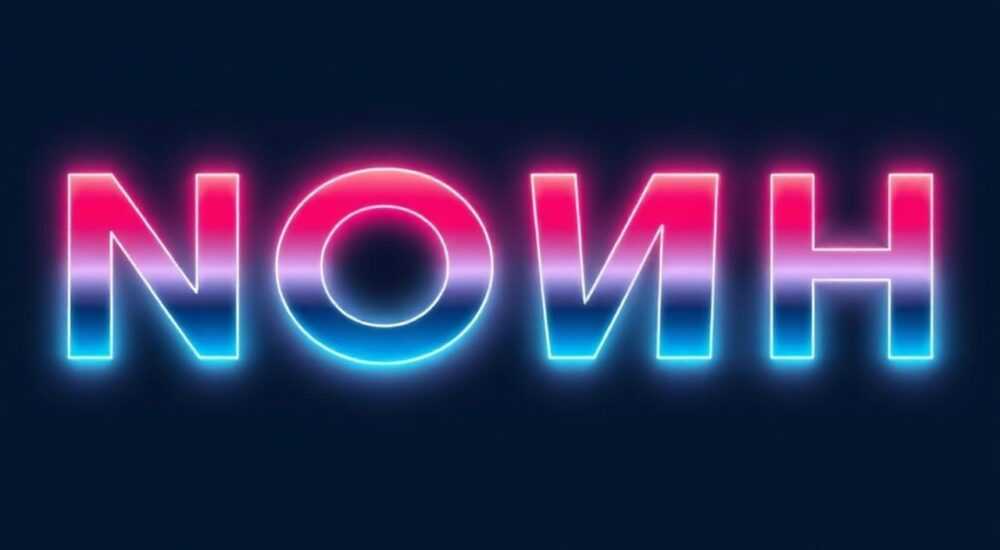
Как сделать шрифт градиентом в фотошопе
Создание градиентных текстов в Photoshop — это мощный инструмент для дизайнеров, который позволяет придать проектам современный и привлекательный вид. Однако многие сталкиваются с проблемой правильного применения этой техники без потери качества и читаемости шрифта. Интересно, что всего несколько лет назад создание градиента на тексте требовало гораздо больше времени и усилий, чем сейчас? В этой статье мы подробно разберем различные методы создания градиентных текстов, их преимущества и особенности применения.
Основные методы создания градиентных текстов
Существует несколько способов сделать градиент на тексте в Photoshop, каждый из которых имеет свои особенности и область применения. Рассмотрим три основных метода:
- Метод наложения слоя-маски: этот подход сохраняет возможность редактирования текста и считается наиболее гибким
- Преобразование текста в форму: позволяет создавать более сложные эффекты, но делает текст неизменяемым
- Использование стилей слоя: быстрый способ добавления градиента через панель Layer Styles
Важно отметить, что выбор метода зависит от конкретных задач проекта и необходимого уровня контроля над конечным результатом.
Пошаговая инструкция: базовый метод создания градиентного текста
Разберем самый популярный метод создания градиентного текста, который подходит для большинства ситуаций:
- Создайте новый документ (Ctrl+N) и выберите подходящий размер холста
- Напишите текст с помощью инструмента Text Tool (T)
- Удерживая Ctrl, кликните по слою с текстом в панели Layers, чтобы загрузить его выделение
- Создайте новый слой (Shift+Ctrl+N) и примените к нему инструмент Gradient Tool (G)
- Настройте параметры градиента в верхней панели инструментов
- Поместите градиентный слой под текстовым и установите режим наложения Multiply
Этот метод гарантирует сохранение возможности редактирования исходного текста, что особенно важно при работе над коммерческими проектами.
Сравнительная таблица методов создания градиентных текстов
Рекомендуемые случаи использования |
Наложение слоя-маски |
Профессиональные проекты, где важна возможность правок |
Преобразование в форму |
Фиксированные элементы дизайна |
Стили слоя |
Быстрые прототипы и простые проекты |
Распространенные ошибки и способы их избежания
При создании градиентных текстов часто допускаются типичные ошибки, которые могут существенно повлиять на качество работы:
- Чрезмерное количество цветов: использование более трех цветов в градиенте обычно приводит к избыточности и ухудшению читаемости
- Неправильное направление градиента: вертикальный градиент чаще воспринимается лучше, чем горизонтальный
- Излишняя контрастность: слишком резкий переход между цветами может вызвать дискомфорт при чтении
Для достижения оптимального результата рекомендуется:
- Использовать 2-3 гармонирующих цвета
- Выбирать направление градиента согласно общему композиционному решению
- Тщательно настраивать точки перехода между цветами
Александр Петров, арт-директор крупного дизайн-агентства с 15-летним опытом работы в сфере графического дизайна, делится своим опытом:
«За годы практики я заметил, что многие начинающие дизайнеры совершают одну и ту же ошибку — они слишком увлекаются эффектами, забывая о функциональности. Когда я создаю градиентный текст, я всегда задаюсь вопросом: ‘Как это повлияет на восприятие сообщения?’ Например, в проекте для крупной торговой сети мы применили тонкий линейный градиент только на первых буквах заголовка, что позволило сохранить баланс между эстетикой и читаемостью.»
Ответы на часто задаваемые вопросы
- Используйте формат SVG для векторной графики
- Да, используя Timeline и ключевые кадры
- При этом важно контролировать скорость изменения
- Рекомендуется тестировать на разных частотах обновления экрана
- Шрифты без засечек с четкими границами
- Не рекомендуется использовать слишком тонкие шрифты
- Оптимальный вес — Medium или Bold
Перспективы развития технологии градиентных текстов
Современные тенденции в веб-дизайне показывают значительный рост интереса к динамическим градиентным текстам. Новые технологии, такие как CSS Grid и переменные CSS, позволяют создавать адаптивные градиентные тексты прямо в браузере. По данным исследования Smashing Magazine 2023 года, использование градиентных текстов в интерфейсах увеличилось на 47% по сравнению с предыдущим годом.
Особенно перспективным направлением является комбинация градиентных текстов с технологиями машинного обучения для автоматической генерации оптимальных цветовых решений. Это позволит создавать более персонализированные и доступные интерфейсы.
Подводя итоги, можно сказать, что создание градиентных текстов в Photoshop — это искусство, требующее как технических навыков, так и художественного чутья. Правильно подобранный метод, внимание к деталям и понимание целевой аудитории помогут создать действительно эффективные дизайнерские решения.